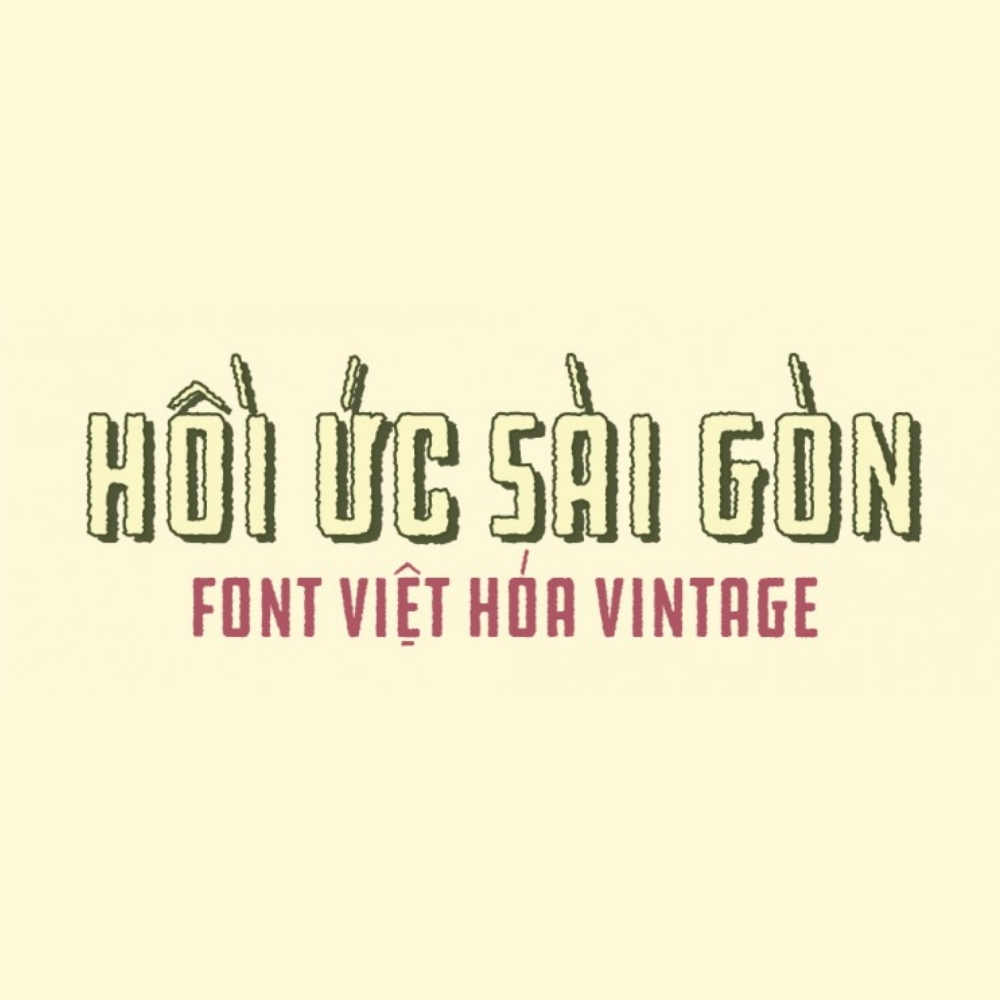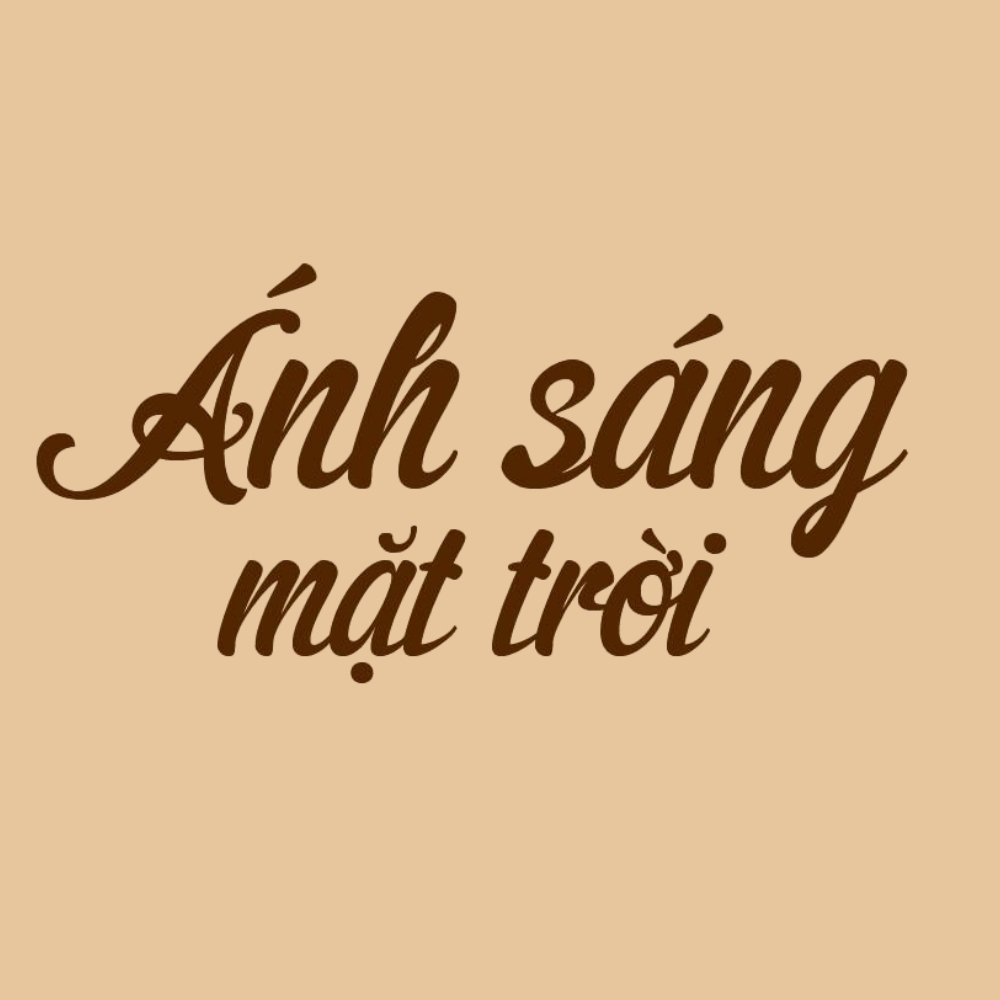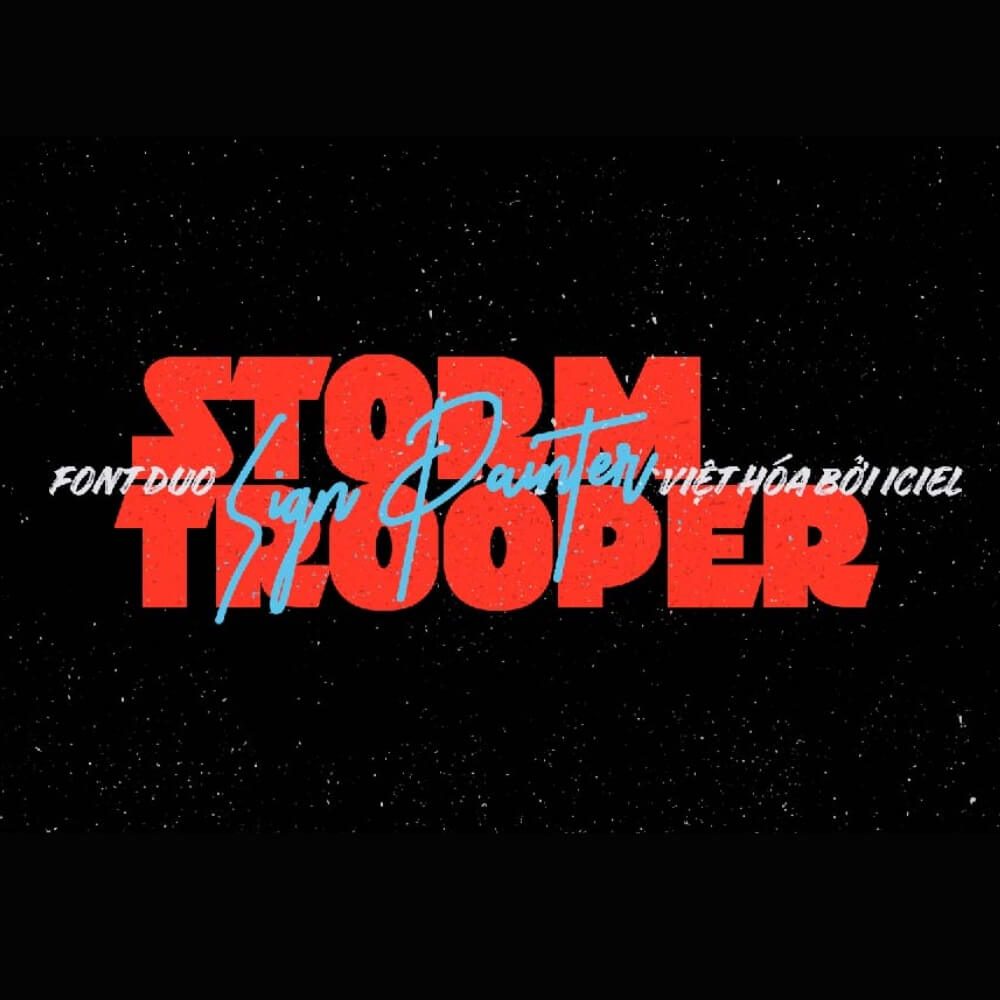
Tải 20+ font Retro Việt hóa cổ điển và miễn phí
Phong cách hoài cổ (Retro/Vintage) đang quay trở lại mạnh mẽ trong các xu hướng thiết kế hiện đại, từ đồ họa, thời trang đến kiến trúc nội thất. Việc sử dụng các bộ font retro Việt hóa không chỉ giúp tái hiện không gian của những thập niên trước mà còn mang lại sự ấm áp, gần gũi và đầy tính nghệ thuật cho tác phẩm.
Đặc trưng thẩm mỹ của các dòng font Retro Việt hóa
Dòng font chữ này thường gợi nhắc đến hình ảnh của các bảng hiệu vẽ tay, những tấm poster quảng cáo cũ hay phong cách thiết kế của thế kỷ 20. Điểm đặc biệt của font việt hóa Retro chính là sự kết hợp giữa những đường nét dày dặn, vững chãi với các chi tiết bo tròn hoặc bo góc đầy tinh tế. Bản Việt hóa giúp giải quyết triệt để vấn đề lỗi dấu tiếng Việt, đảm bảo các ký tự đặc biệt luôn hiển thị đồng bộ và giữ đúng tinh thần của bộ chữ gốc.
Bên cạnh yếu tố hình khối, font Vintage Việt Nam còn sở hữu khả năng truyền tải thông điệp về sự bền vững và giá trị truyền thống. Những bộ Retro font script với nét chữ uốn lượn thường mang lại cảm giác lãng mạn, trong khi các kiểu chữ sans-serif đậm lại tạo nên sự mạnh mẽ và chuyên nghiệp. Sự đa dạng này cho phép người thiết kế linh hoạt thay đổi phong cách từ hoài niệm, nhẹ nhàng đến phá cách, độc đáo cho từng dự án cụ thể.
Gợi ý phối màu: Để phong cách font Retro Vintage phát huy hiệu quả thị giác cao, bạn nên phối hợp với các tông màu trầm như vàng nghệ, cam cháy, xanh rêu hoặc đỏ bordeaux. Việc sử dụng thêm các hiệu ứng nhiễu (grain) hoặc vết xước nhẹ sẽ giúp thiết kế trông thật và giàu cảm xúc hơn.
03 Ứng dụng của font chữ Vintage Việt hóa trong thiết kế và đời sống
Với vẻ ngoài đậm chất nghệ thuật, các bộ font này mang lại giá trị thẩm mỹ ổn định khi được đưa vào thực tế trang trí và quảng bá công trình:
• Bảng hiệu cho Homestay và Cafe: Những nét chữ của font chữ Vintage Việt hóa rất ăn ý khi xuất hiện trên bảng hiệu bằng gỗ, kẽm hoặc alu phủ màu trung tính. Đối với các dự án nhà lắp ghép nghỉ dưỡng, font chữ này giúp không gian trở nên ấm cúng và thu hút du khách yêu thích vẻ đẹp xưa cũ.
• Nhận diện thương hiệu cho sản phẩm thủ công: Sử dụng Retro font script trên bao bì trà, cafe hoặc các món đồ handmade giúp tăng giá trị nhận diện thương hiệu và tạo cảm giác về sự tỉ mỉ, chất lượng trong từng sản phẩm.
• Thiết kế Poster và truyền thông số: Font Retro Việt hóa Canva là lựa chọn phổ biến cho các bài đăng mạng xã hội hoặc banner sự kiện mang chủ đề hoài niệm, giúp tạo ra sự khác biệt so với các phong cách thiết kế phẳng hiện đại.
03 Lưu ý để thiết kế hài hòa với phong cách Retro Vintage
Để khai thác hiệu quả vẻ đẹp của dòng Vintage Retro font mà không làm rối mắt người xem, người thiết kế nên lưu tâm một số điểm sau:
• Cân đối mật độ chữ: Các font Retro thường có nét chữ dày và chiếm diện tích. Bạn nên nới rộng khoảng cách giữa các chữ cái (tracking) để văn bản thông thoáng và dễ đọc hơn, tránh cảm giác bết dính khi nhìn từ xa.
• Sử dụng làm điểm nhấn chính: Không nên dùng font chữ Vintage Việt hóa free cho các đoạn văn bản hướng dẫn dài hay hồ sơ kỹ thuật. Hãy để nó xuất hiện ở vị trí tiêu đề, slogan hoặc các cụm từ quan trọng để tạo trọng tâm cho bản vẽ.
• Kết hợp font chữ thông minh: Sự tương phản giữa một font Retro đậm và một font sans-serif mảnh hiện đại sẽ giúp bố cục trở nên chuyên nghiệp và tinh tế, tránh tình trạng thiết kế bị quá tải bởi các chi tiết cổ điển.